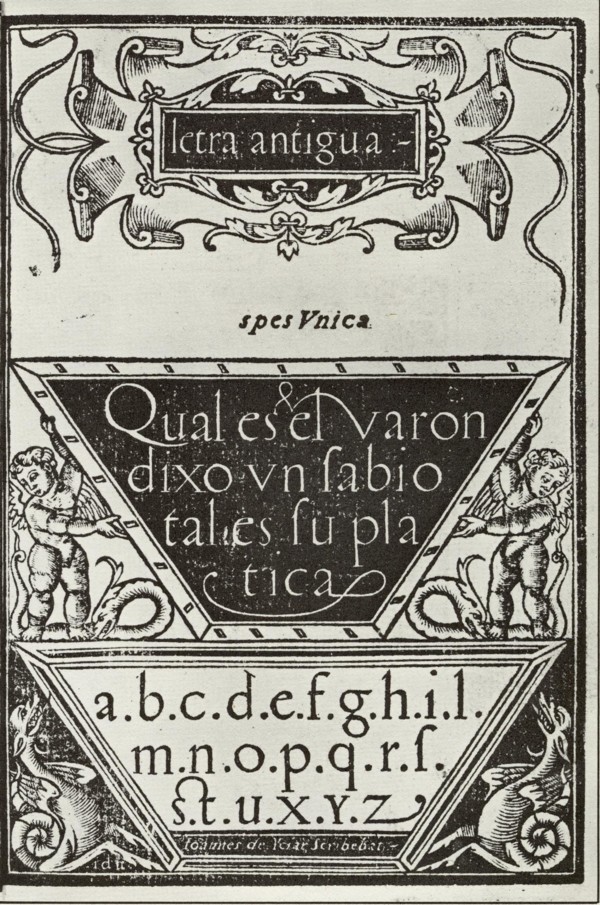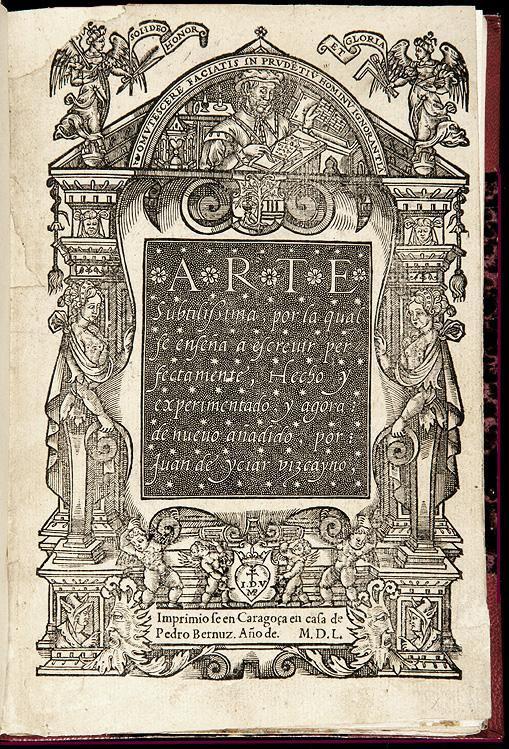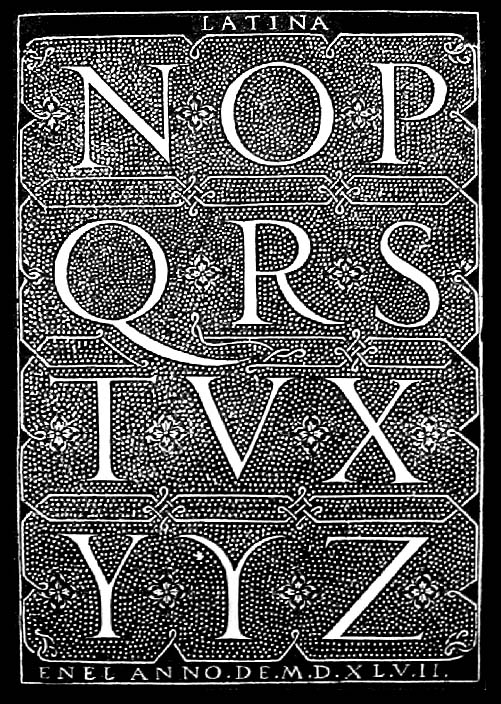
Juan de Yciar (1515(23?) 1590)Matemático e calígrafo basco, autor da Arte Subtilissima.
Este insigne vascongado, nació en Durango (Vizcaya) el año 1523; fue el primer calígrafo «que entre nosotros dio y publicó reglas sobre el arte de escribir». Estudió con gran provecho a los calígrafos italianos Henricis, Tagriente y Palatino, o inspirándose en las bellezas de la letra bastarda italiana, aldina y grifa, inventó la letra llamada bastarda española, que todavía usamos... (Citação de: Arte de la Escritura y de la Caligrafía (Teoría y práctica) Rufino Blanco y Sánchez) Fue maestro en Zaragoza, y allí escribió y grabó en madera190 su obra, que contiene no pocas bellezas gráficas. A más de la letra bastarda que el Vizcaíno inventó, de la cual es una muestra la página siguiente, escribió varias letras cancellarescas, antiguas, de privilegios, buláticas y de breves, todas magistralmente hechas. Son muy notables también las letras de adorno, las de libros de coro y la letra blanca, compuestas por el insigne Icíar. En su obra se leen algunas observaciones teóricas, que tienen el valor de ser las primeras de la Caligrafía española. PublicaçõesYciar, Juan de. Arte Subtilissima. Facsimile of the 1550 edition / Juan de Yciar ; with a translation by Evelyn Shuckburgh and an introduction by Reynolds Stone. London, Oxford University Press, 1960.
Yciar, Juan de. Arte breve y provechoso de cuenta castellana y arithmética : donde se muestran las cinco reglas de guarismo por la cuenta castellana, y reglas de memoria,... / [Juan de Yciar]; Fué impresa la presente obra en la muy noble y leal ciudad de Caragoça, en case de la viuda de Estevan de Nagera, a costa. Inscrição: Joannes de Yciar aetatis sue anno XXV, d'après Brunet, qui signale sous ce titre une 2e partie de l'Arte subtilissima... publiée en 1555. Yciar, Juan de. Libro subtilissimo por el qual se enseña a escreuir y contar pfectamete el qual lleua el mesmo orden que lleua vn maestro con su discipulo de Icíar, Juan de, n.1523? Orthographia Practica, 1547 |